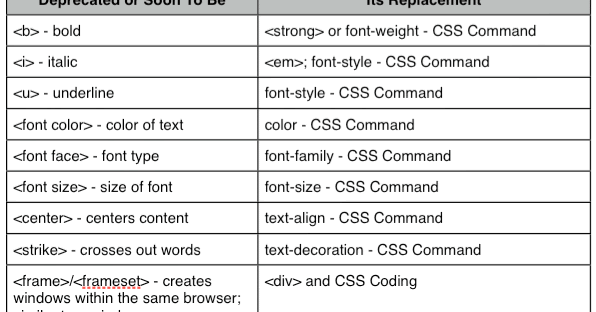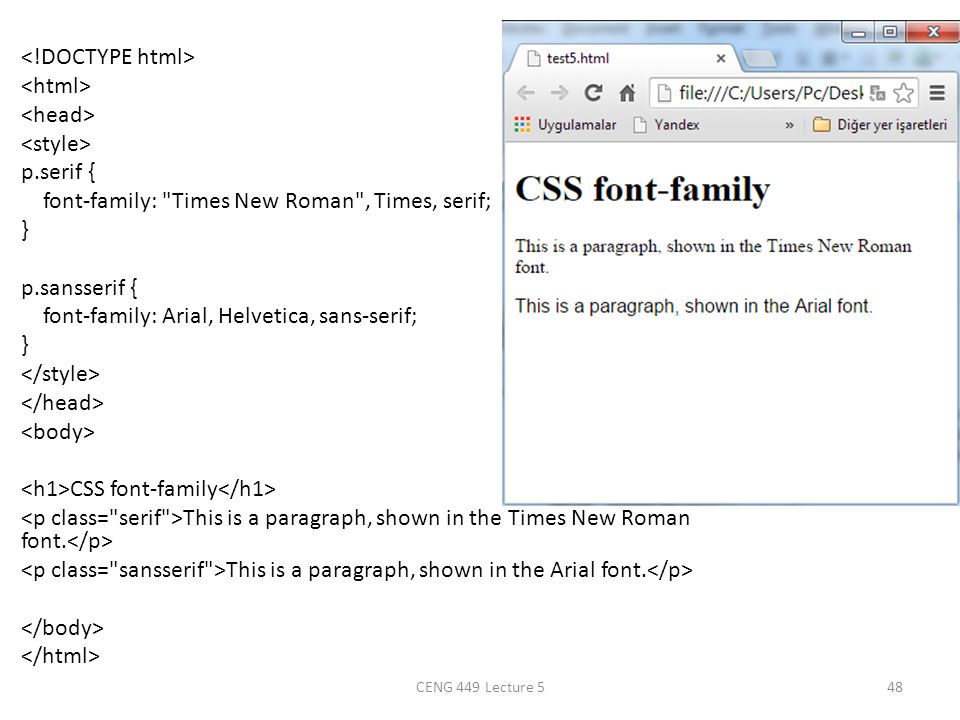
Аннотация: Эта лекция строится на основе полученных ранее в этом курсе знаний, предоставляя подробное руководство по эффективному оформлению текста с помощью CSS.
Введение
Так как Web является совокупностью документов — динамических, статических, функциональных — соглашения, согласно которым они форматируются, заимствуются из лучшего доступного нам источника: шести веков традиции печати. Это включает полиграфию. Однако Web является новой и отличающейся информационной средой, а полиграфия Web-сайта требует по большому счету совершенно других навыков для создания представления, и зависит от дополнительных ограничений.
Эта лекция строится на основе полученных ранее в этом курсе знаний, предоставляя подробное руководство по эффективному оформлению текста с помощью CSS.
Обзор полиграфии Web
Другими темами, которые заслуживают дополнительного рассмотрения, являются контраст, разборчивость и удобочитаемость — сейчас мы этим займемся.
Контраст
Контраст печати, легкость, с которой каждый отрывок можно отличить от пробелов и смежных отрывков, зависит от ряда факторов, таких как освещенность, цвет, размер, и композиция. Он упоминается здесь, чтобы обратить внимание, что слабоконтрастная копия должна задаваться с максимально применимым размером шрифта.
Разборчивость и удобочитаемость
| Цель | Длина строки | Пространство между столбцами текста и расстояние между строками | Выбор шрифта | Выравнивание |
|---|---|---|---|---|
| Удобочитаемость | средняя | увеличенная | с засечками | невыровненный справа [слева] |
| Разборчивость | короткая | нормальная | без засечек | переменное, часто полное |
Свойства шрифта CSS: изменение внешнего вида текста
Подготовка текста включает манипуляции с текстом в отношении, как композиции, так и внешнего вида отдельных букв и слов. Последний класс задач реализуется свойствами шрифта CSS, которые будут рассмотрены ниже.
Размер шрифта и выбор единиц измерения
Так как документы обычно изменяют размер шрифта чаще чем гарнитуру, и варианты шрифтов обычно хорошо обрабатываются таблицами стилей агентов пользователей, то основным интересующим нас свойством является font-size. При использовании в правиле за ним следует значение, которое определяет единицу измерения, или иногда ключевое слово размера (такое как small или medium )
Как это делается
Самое важное объявление font-size в таблице стилей выглядит примерно следующим образом:
body {…
font-size: 14px;
…}intuit.ru/2010/edi»>Наследование заставляет всевозможные спецификации размера в документе основываться на размере, объявленном для тела документа, будут ли это таблицы стилей браузера или ваши собственные.
Типичное значение в браузерах по умолчанию, равное 16 пикселям, является хорошей исходной точкой для размера основного текста, но большинство посетителей смогут легко прочитать и меньший шрифт. В результате многие дизайнеры выбирают меньший размер — около 11 -14 пикселей.